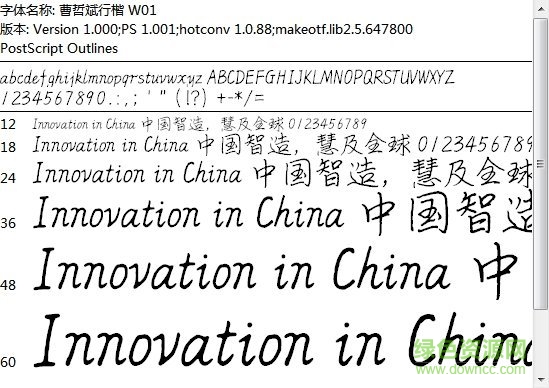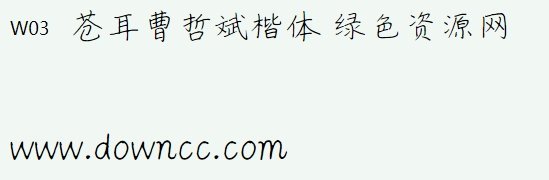
蒼耳曹哲斌楷體是蒼耳字庫推出的一款行楷字體,以楷書字體為主,兼具手寫字體特色,給人短小清秀的毛筆字體美感,字跡清晰流暢,十分得體,綠色資源網(wǎng)誠意推薦!
倉耳曹哲斌行楷,即倉耳曹哲斌楷書,是一款手寫楷體字庫。字體的筆畫流暢大方,筆型圓潤飽滿,結(jié)構(gòu)清晰,美觀與實(shí)用兼?zhèn)洌哂歇?dú)特的書法韻味。
曹哲斌行楷字體是在曹哲斌楷書字體上更新升級而來,完整了繁體字庫,筆畫更顯纖細(xì),字形突出,多種符號的美化讓文字更有韻味,可以運(yùn)用在藝術(shù)設(shè)計(jì)、平面設(shè)計(jì)、海報(bào)設(shè)計(jì)等多種場合。